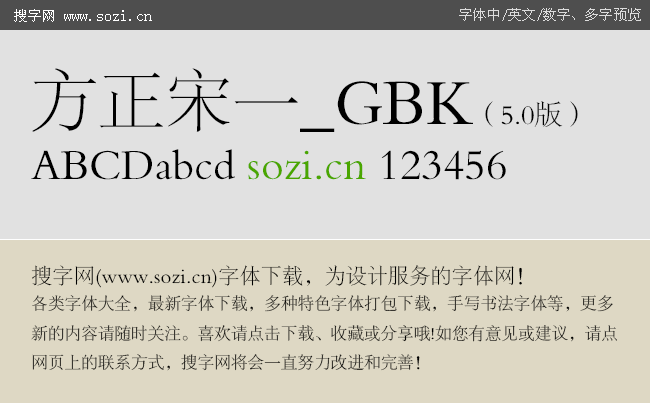
方正宋一-GBK
搜字網(wǎng)提供一款方正宋一字體下載,方正宋一是一款應(yīng)用于設(shè)計(jì)方面的中文簡體漢字,該字體纖細(xì)大方,端正得體,并且整體效果非常出色,能夠適用于廣告設(shè)計(jì)、名片設(shè)計(jì)、包裝印刷、產(chǎn)品設(shè)計(jì)等應(yīng)用,有喜歡的朋友可免費(fèi)下載收藏。